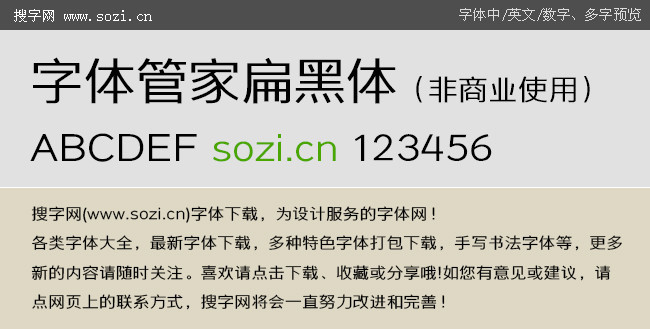
字體管家扁黑體(非商業(yè)使用)
搜字網(wǎng)給大家提供一款字體管家扁黑體(非商業(yè)使用)中文字體下載,字體管家扁黑體較常用的黑體略扁,字形端正易讀,又十分工整簡潔,適合海報設(shè)計、包裝畫冊等宣傳廣告等應(yīng)用(此字體為個人非商用版,商用可以聯(lián)系QQ:1006760504)。